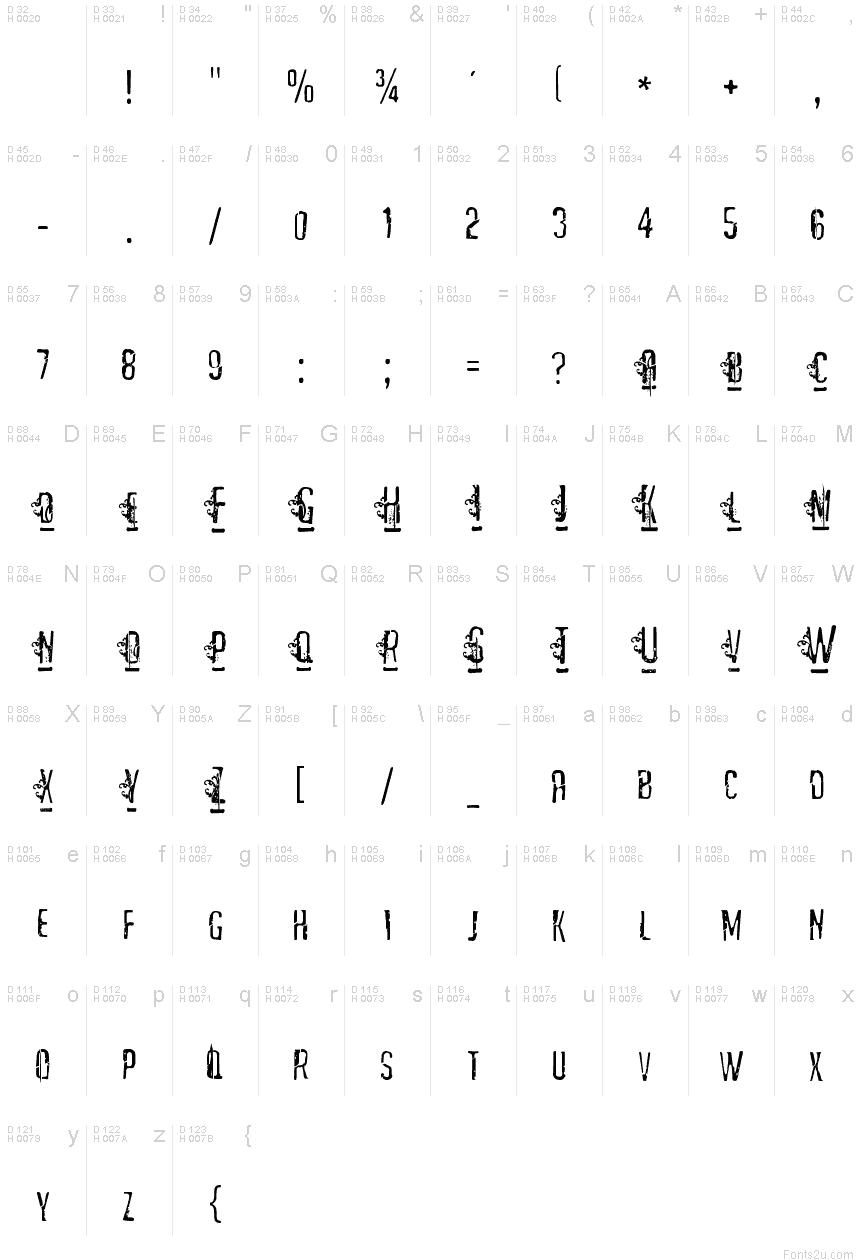
Matejo من Bumbayo Recordz هو خط عرض مجاني متآكل بطابع ملصقات غامضة (غوثيك). تبدو الحروف كأنها مخدوشة وملطخة ومشوهة قليلاً، حيث تمزج بين الأشكال التقليدية الطويلة والحواف الخشنة وبعض الزخارف، مما يمنح النص مظهراً مسكوناً بدلاً من مجرد كونه مهترئاً.
وهذا ما يجعل هذا الخط المجاني خياراً طبيعياً لملصقات الرعب، ومنشورات موسيقى الأندرغراوند، وأغلفة المجلات، وعناوين الألعاب، وتصاميم الفعاليات حيث تحتاج الحروف إلى أن تبدو غير مستقرة ومسرحية. كما أنه يعمل بشكل رائع للعناوين القصيرة والشعارات، لأن الملمس المتضرر والصورة الظلية غير المنتظمة تضفي طابعاً غنياً بالأجواء دون الحاجة إلى الكثير من النصوص.